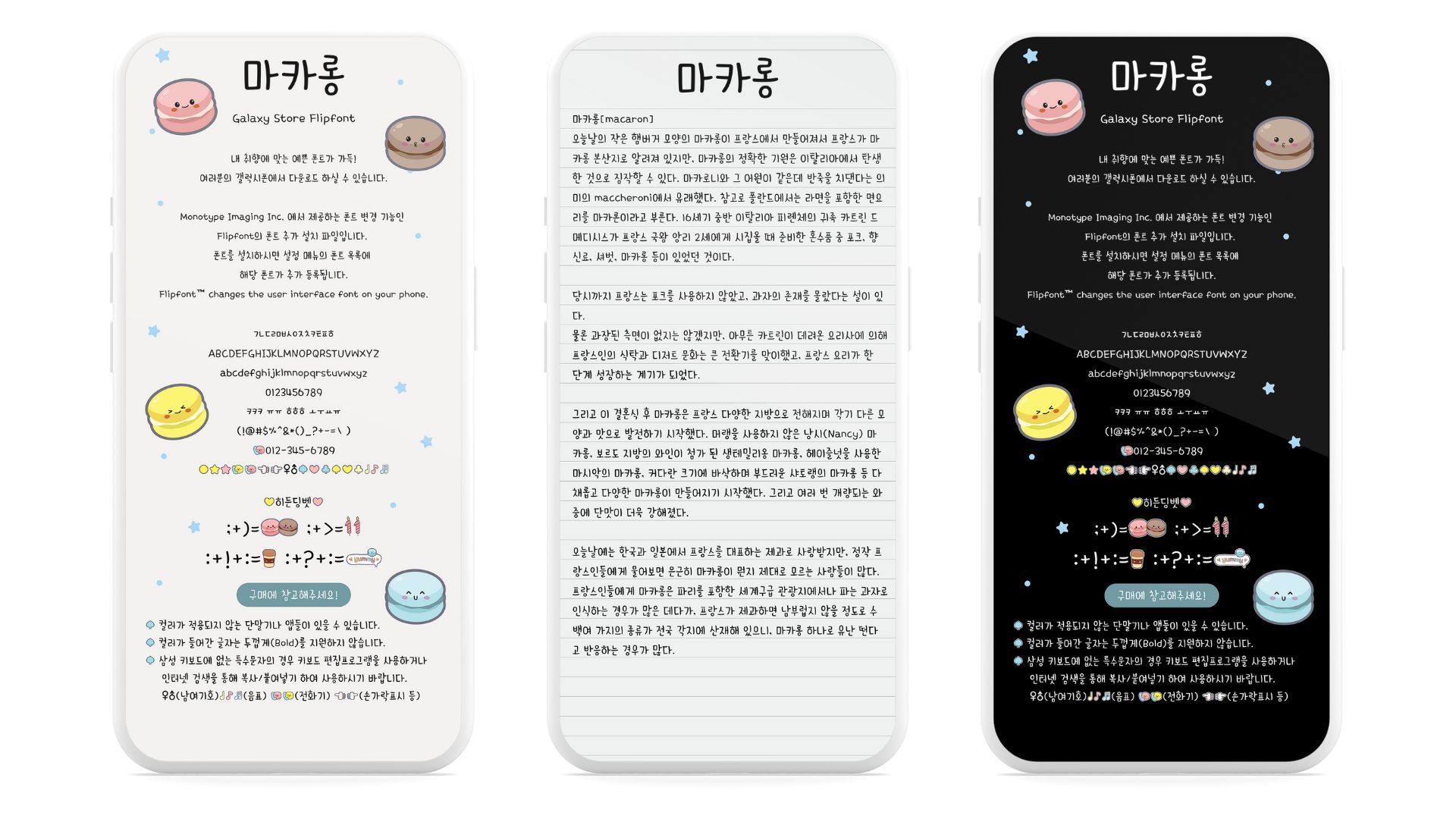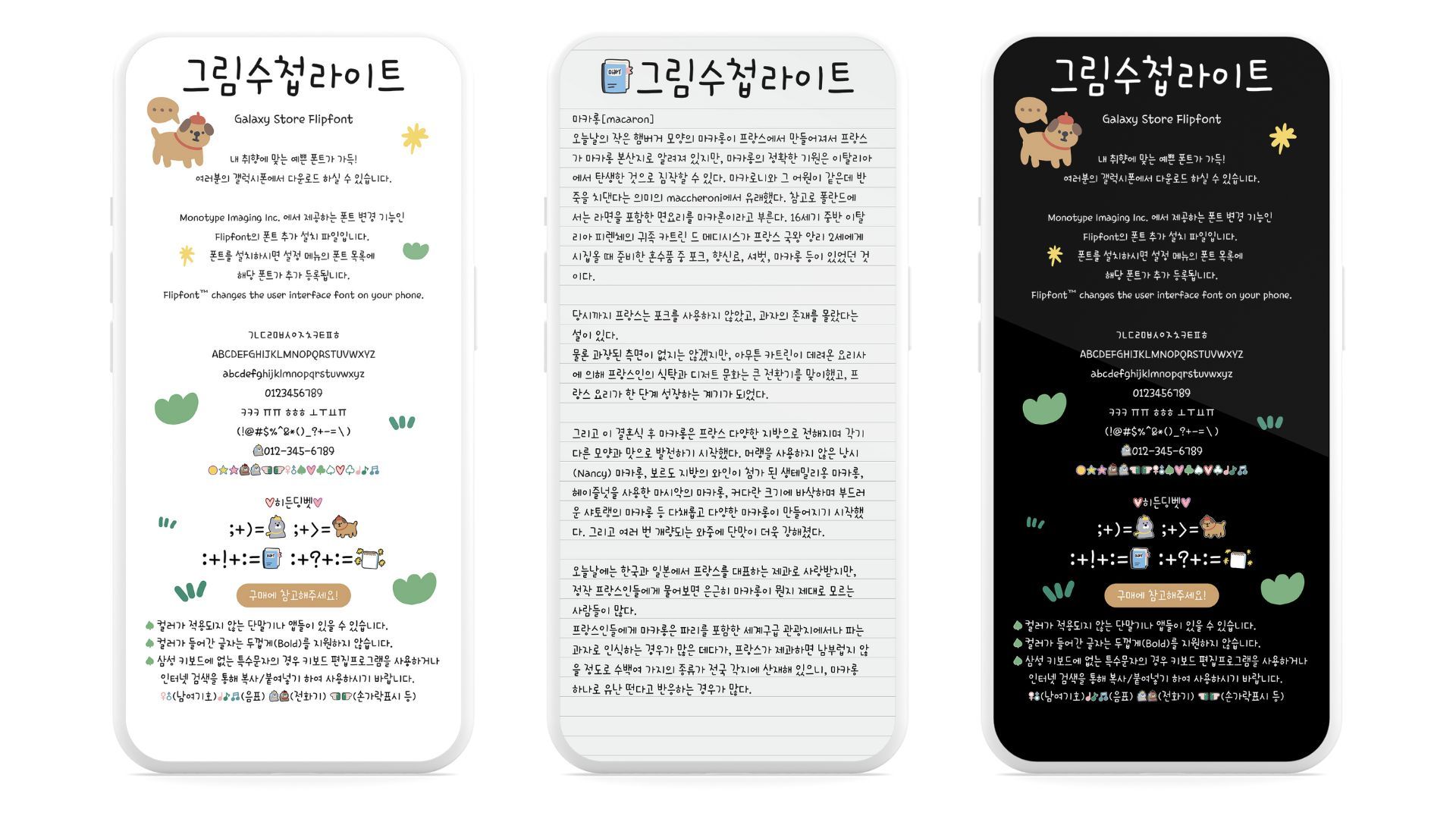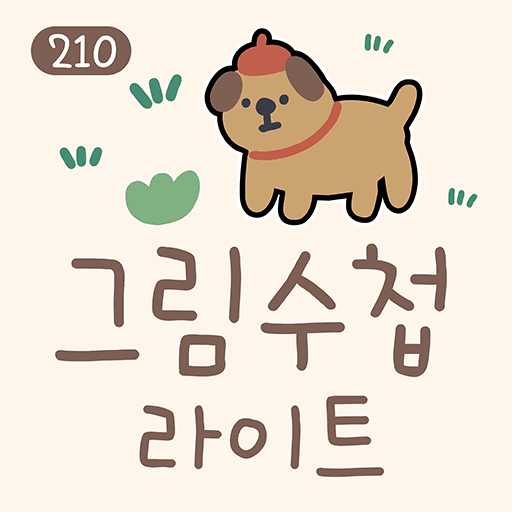
빼빼로 데이에 돌아온 귀여운 마카롱 폰트!사인펜으로 쓴 듯한 손글씨와 달콤한 딩벳이 함께 있어요!달콤한 마카롱을 서체로 늘 느껴보세요!기존의 210마카롱보다 가독성도 올라갔고 컬러딩벳도 추가되었어요!
많은 분들께서 기다려주신 그림수첩이 라이트로 돌아왔어요! 여행가서나 방학때처럼 수첩에 그림으로 낙서하듯 써내려간 손글씨 폰트에요!초성은 큼직큼직하고 종성은 작게그려져서 어릴 떄 쓴 글씨처럼 귀엽답니다!기존의 210그림수첩보다 가독성도 올라갔고 컬러딩벳도 추가되었어요!